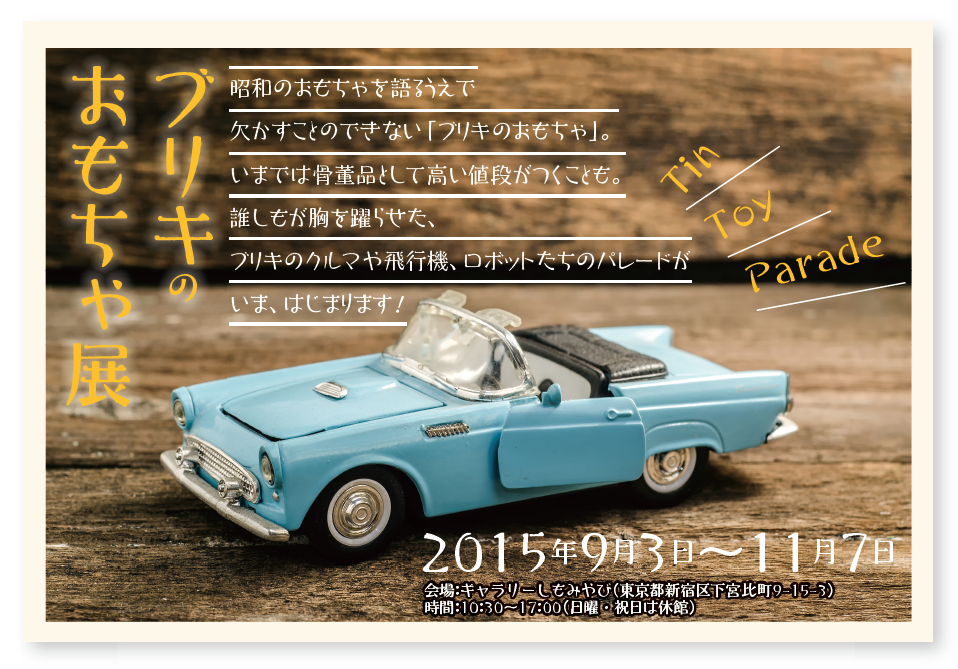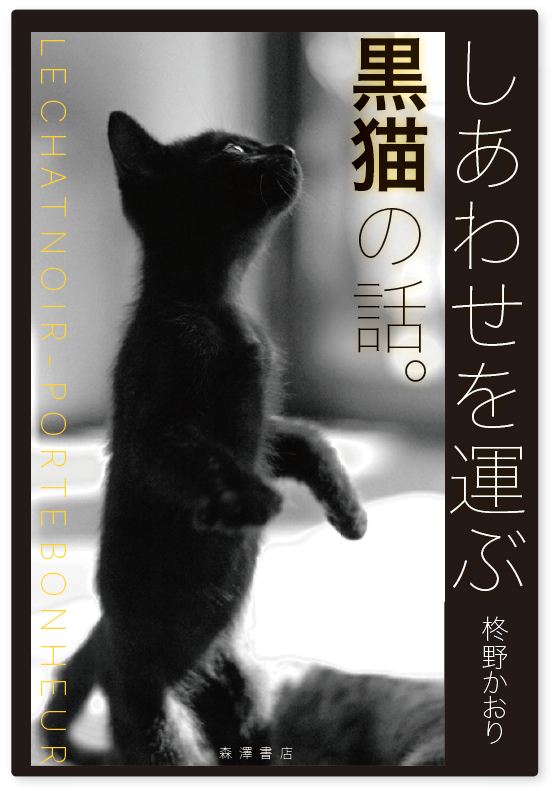
「凸版文久見出し明朝 EB」は、装幀やエディトリアルデザインのタイトルなど、大きなサイズで使われることを想定した見出し書体です。和欧文ともに縦画・横画に明快にコントラストをつけ、筆文字のような緩急や抑揚により、力強さの中に優雅さを感じさせるデザインに仕上げることで、伝統的でオーソドックスな形を継承しながら、時流にあったインパクトのある見出し用書体を実現しています。
はらいの右上から左下への滑らかなシルエットが特徴です。
縦画は少し強めの起筆になっており、ゆったりとした左払いが特徴的です。
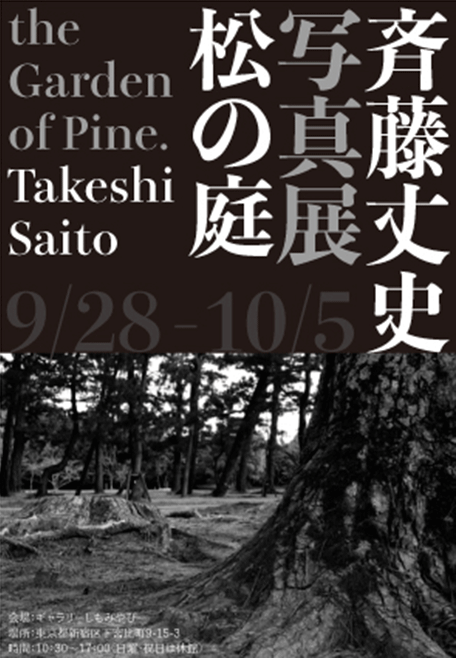
「凸版文久ゴシック R」は横組みでの使用に特化して作られた本文用ゴシック体で、文字が持つ本来の形を活かした抑揚のあるデザインが特徴で、文章を読むリズムを演出するように設計されています。書籍はもとより、横書きで日本語を読む機会が多い電子媒体などでも、長文をテンポよく読み進めることができます。英数字は昨年リリースされた「凸版文久明朝 R」と共通のデザインコンセプトを採用しているため、凸版文久体シリーズを使用した統一感のあるデザインイメージの演出が可能になります。
漢字に比べてひらがな、カタカナを小さく設計することで文字に心地よいリズムを作り出し、テキストのラインに抑揚をつけています。
一般的なゴシック体では、線の入りの部分の突起は右についていますが、「凸版文久ゴシック」では、明朝体と同じように左についています。
(左)凸版文久明朝(中)凸版文久ゴシックR(右)従来の凸版書体
「はせミン」は、手書き風の風合いに、明朝体のウロコのようなアクセントを持たせたデザイン書体です。漢字はスクエアで落ち着いた骨格を持ちながらも、ひらがなは遊び心のあるリズミカルなデザインになっているため、ポップで柔らかい印象を与えながらも、文章をしっかりと読んでいただけます。ウエイトはR/M/Bの3種類があり、縦画と横画が同等の太さのRに対して、縦画が太くなっていくM、Bの設計にも特徴があります。
筆の入荷は●、止め部部には参画のような鱗が特徴です。
「ヒラギノ角ゴ W0」は、ヒラギノ角ゴの基本的な骨格を活かしたまま、限りなく画線を細らせており、これまでで最も細い「ヒラギノ角ゴ W1」の約半分の線幅で設計された書体です。画線の先端にアクセントのあるヒラギノ角ゴの特徴を受け継ぎ、クールでスマートな表情に仕上がっています。見出しやキャッチコピーを大きくかつ軽やかに入れたい時、Webページの文字をスタイリッシュに見せたい時などに使用することで、クリアで洗練された印象に仕上げることができます。